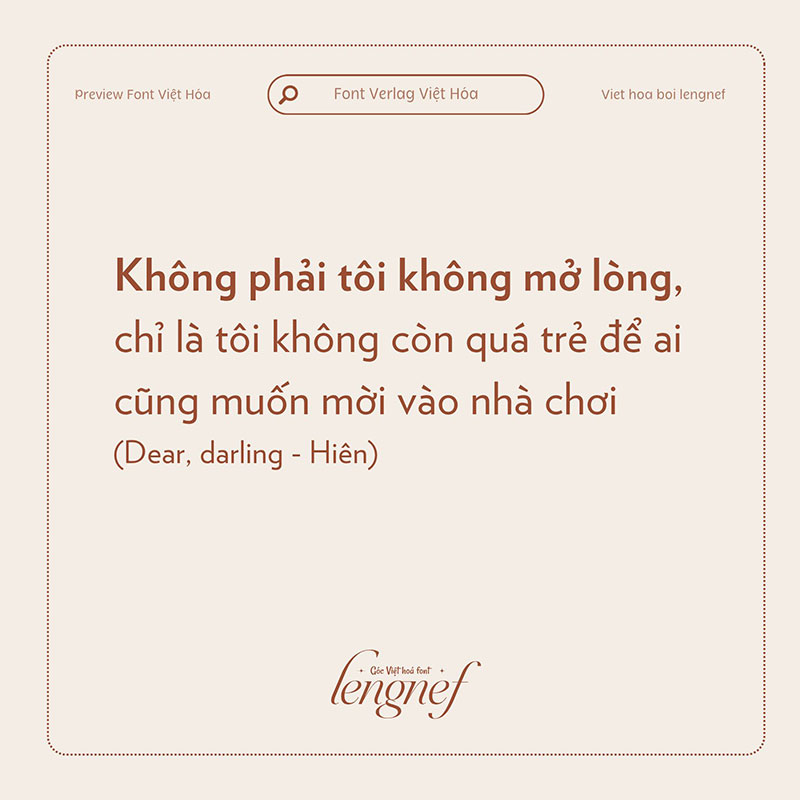
- Tác giả: Hoefler&Co
Bộ phông chữ Verlag là một trong những phông chữ sans serif hình học. Nếu bạn đang tìm kiếm những phông chữ ấn tượng thì Verlag sẽ là lựa chọn lý tưởng, phông được thiết kế đặc biệt để sử dụng tại bảo tàng Guggenheim trước khi được hai nhà thiết kế phông chữ nổi tiếng thiết kế lại vào năm 2006. Bên cạnh những đặc điểm cơ bản như vẻ ngoài chắc chắn, ổn định và đáng tin cậy, phông chữ này phù hợp cho việc in ấn và thiết kế.